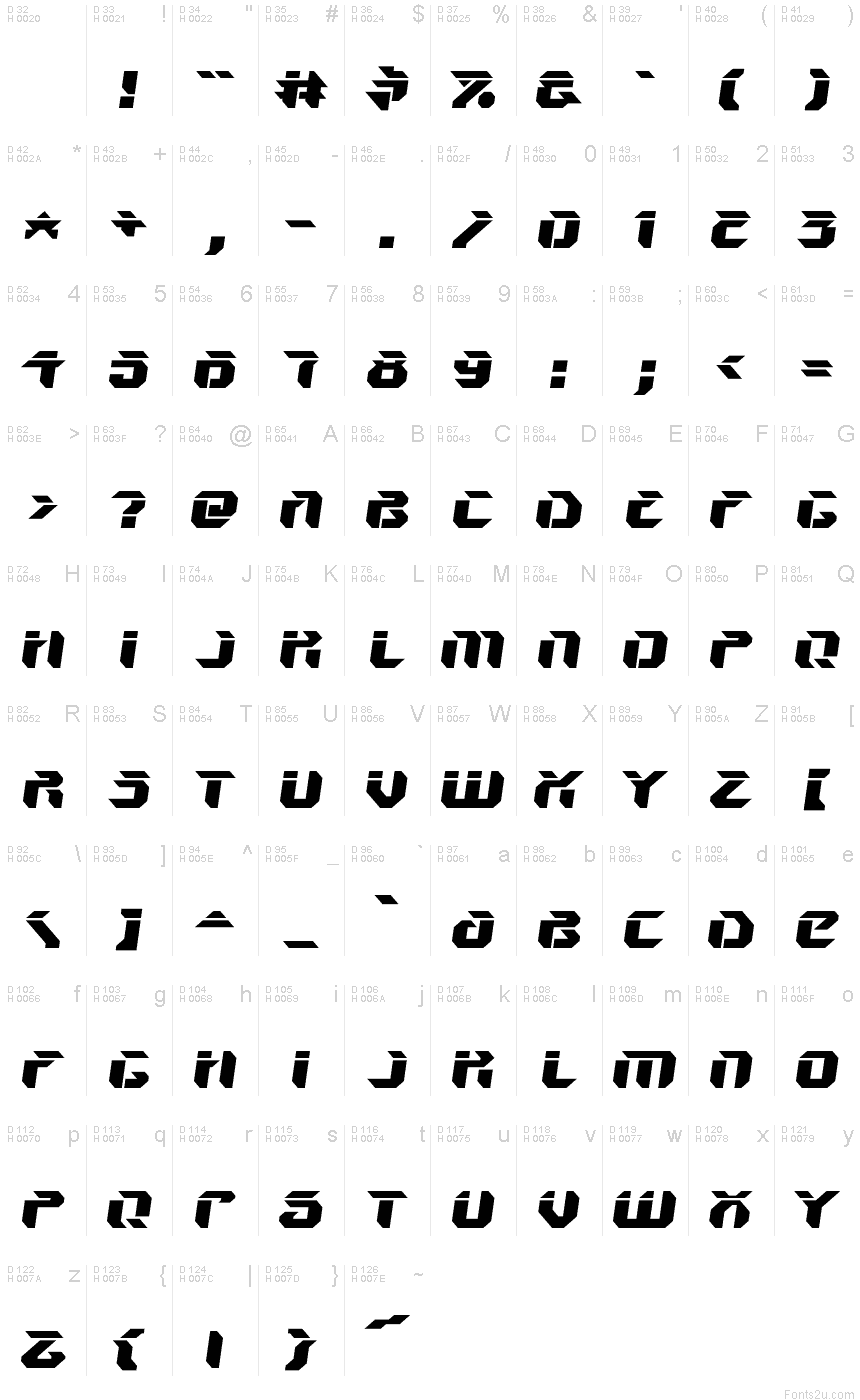
V5 Ampon Slanted di Roberto Christen è un font display techno futuristico gratuito, dal carattere tagliente e inclinato in avanti. Le lettere sono costruite con tagli geometrici massicci e angoli netti, creando un ritmo meccanico e compatto che affonda le radici nella grafica digitale della fine degli anni '90, piuttosto che nella fantascienza minimalista e levigata.
Si adatta perfettamente a loghi gaming, flyer da club, copertine di musica elettronica, titoli di poster e progetti di branding dove serve un font gratuito che proietti movimento e un'estetica sintetica. Usalo per titoli, schede di presentazione o wordmark incisivi, specialmente quando vuoi che le forme inclinate e le nette interruzioni diagonali facciano la parte del leone nel design.